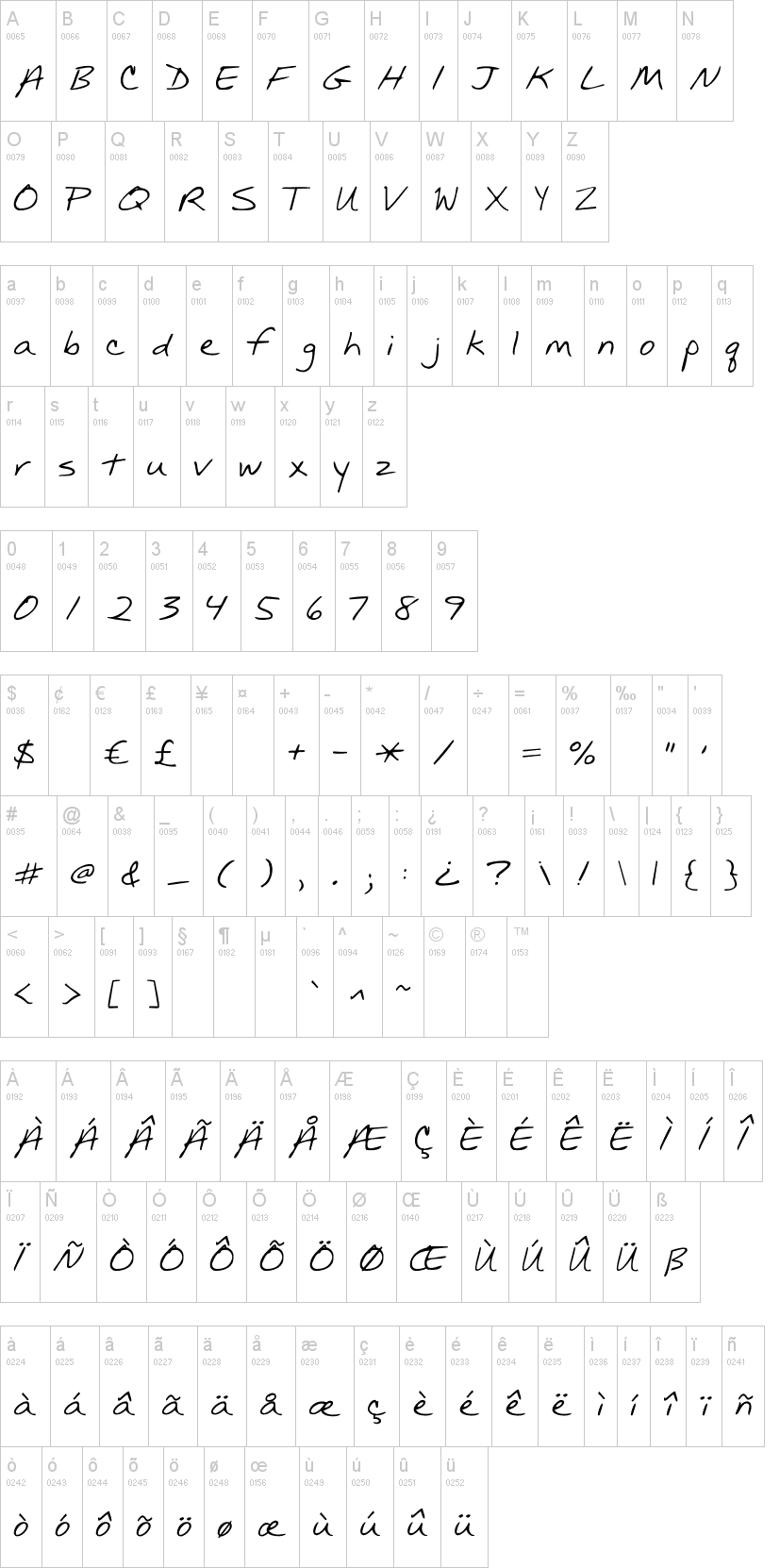
KG Mullally 是一种英文字体,它由英国设计师 Kevin G. Mullally 开发,它是一种细腻的手写体字体,具有柔和的线条,充满活力,非常适合用于设计海报、标志、卡片等。KG Mullally 字体具有多种字形,可以满足不同的设计需求,它还可以用于印刷材料,以及网页和数字媒体设计。KG Mullally 字体可以免费使用,也可以付费购买,付费版本提供更多的字形,可以满足更多的设计需求。内容介绍
KG Mullally是一款非常不错的手写艺术字体,具有很好的视觉感,适合于文化类的宣传设计、商业类品牌的广告和产品包装设计以及个性化文字排版等较多场景。